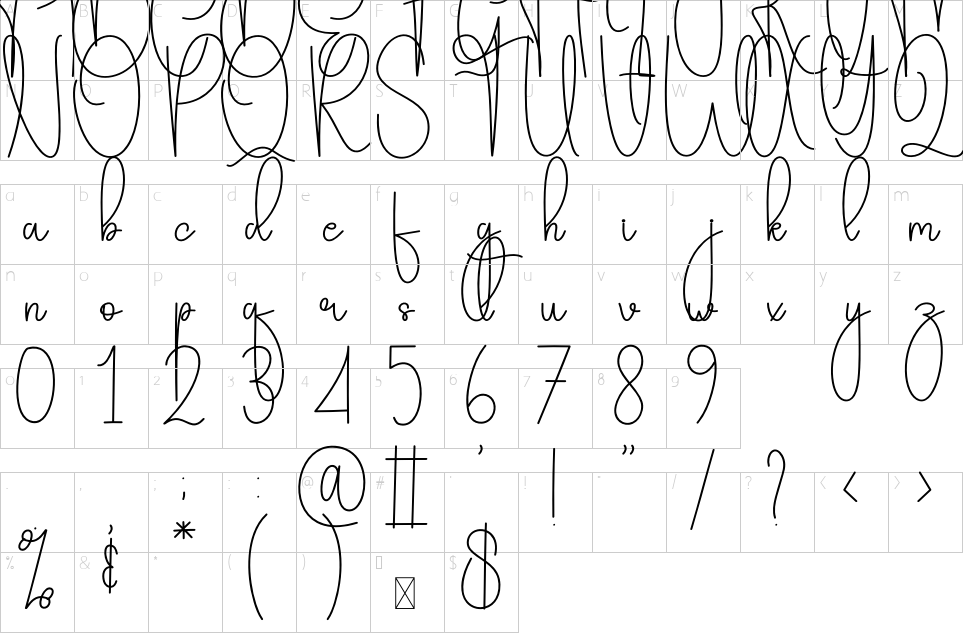
A fonte Adventure é uma escolha perfeita para quem está buscando uma fonte gráfica que se destaca tanto quanto seus projetos. Ela foi criada por William Jhordy e vem trazer um estilo leve e animado, adequado para gráficos criativos e interativos. Suas linhas curvas e espaçamento equilibrado permitem uma variedade de usos, desde o design de materiais para crianças até o design de logotipos, tornando-a uma ótima opção para quem deseja dar um toque de alegria e diversão em seus projetos digitais. Com uma design sólido e funcional, Adventure se destaca como uma fonte gráfica gratuita, acessível para download tanto no Windows quanto no Mac. Com base nas 190 downloads que a fonte já teve, é evidente que muitos usuários estão adotando Adventure para dar um toque especial às suas criações digitais.